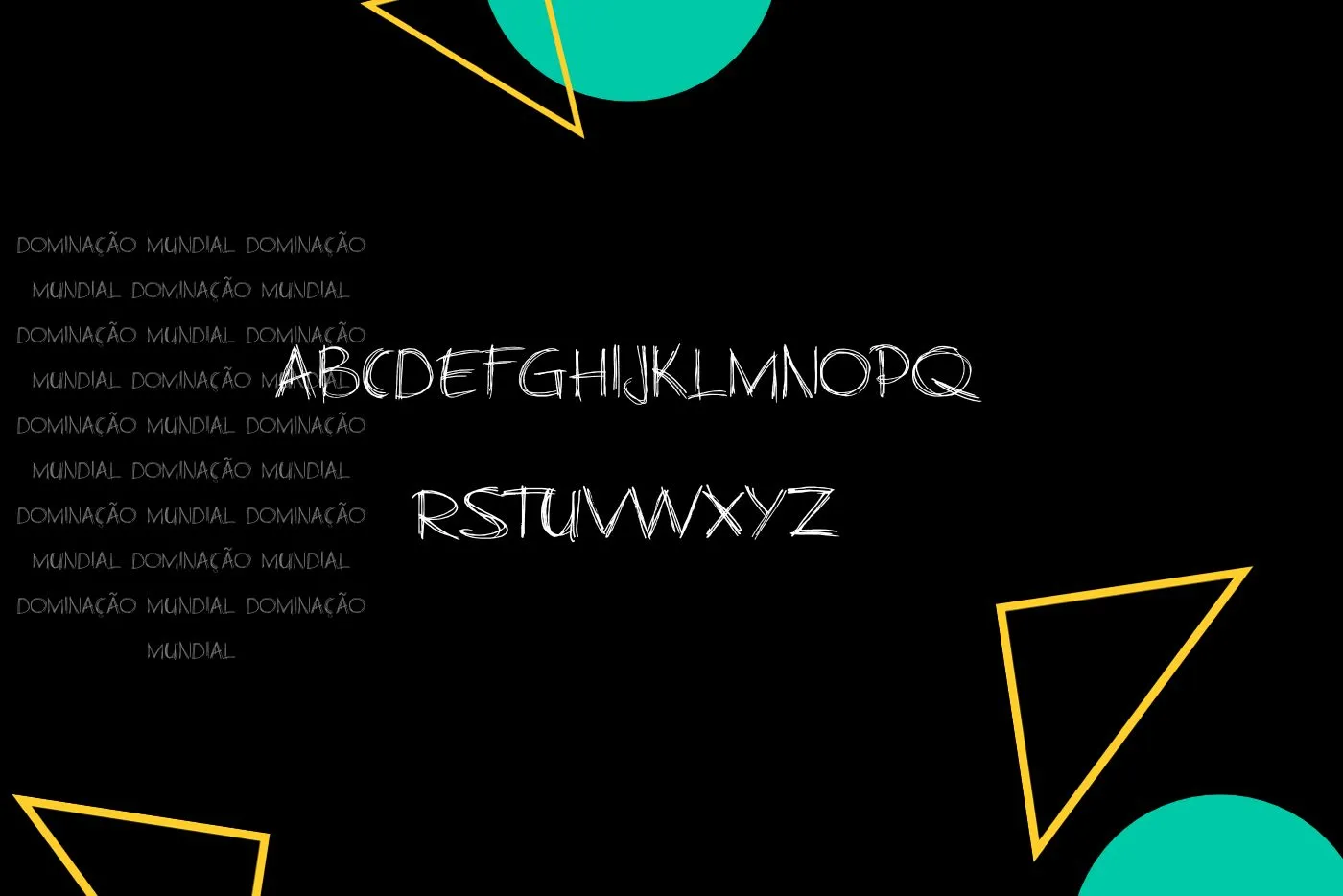
A fonte Business As Usual é uma fonte de script. Foi desenhado por Hanoded e é uma escolha que se destaca pelo seu carácter sério e profissional. Seu design é uma combinação de formas geométricas e linhas limpas que lhe conferem um aspecto moderno e organizado. É perfeito para combinar com sua alternativa. Fonte Road Rage é mais adequado para esse propósito. Esta fonte é particularmente adequada para uso em contextos empresariais e corporativos, onde a comunicação precisa transmitir confiabilidade e seriedade.
Uma das características marcantes desta fonte é sua legibilidade. As letras são cuidadosamente projetadas para garantir que cada caractere seja facilmente reconhecido, tornando-as uma escolha sólida para documentos, relatórios e materiais de marketing que precisam comunicar informações de forma clara e eficaz. Seus caracteres são consistentes e bem espaçados, garantindo que o texto fique visualmente equilibrado e de fácil leitura em diferentes tamanhos e mídias.
Emparelhamento Com a Fonte Business As Usual
Para uma combinação eficaz, é importante escolher uma fonte secundária que complemente seu estilo limpo e profissional. Aqui estão algumas opções de emparelhamento que podem funcionar bem:
- Fonte Arial: É uma fonte sem serifa amplamente reconhecida por sua legibilidade e simplicidade. Ele pode ser usado para títulos e cabeçalhos em combinação para criar um contraste entre os elementos proeminentes e o corpo do texto.
- Fonte Geórgia: É uma fonte serifada que pode criar um contraste interessante. É especialmente adequado para uso em documentos impressos, proporcionando uma sensação de formalidade e sofisticação.
- Fonte Open Sans: É uma fonte sem serifa fácil de usar que equilibra perfeitamente a legibilidade com um toque de modernidade. Pode ser usado para criar um contraste suave em materiais de marketing e apresentações.
Família de Fontes Business As Usual
- Business As Usual Regular
Melhores Usos da Fonte Business As Usual
As melhores e mais utilizadas aplicações desta fonte são:
- Logos e marcas de luxo.
- Títulos em materiais impressos e digitais.
- Design de moda e etiquetas de produtos.
- Convites e papelaria elegante.
- Campanhas publicitárias glamorosas.
- Posts e conteúdo de mídia social marcante.
- Embalagens de produtos de alta qualidade.
- Letreiros e placas em estabelecimentos comerciais.
- Criação de arte tipográfica personalizada.
- Títulos de matérias em revistas e livros.
Vista da Fonte Business As Usual
Qual é a fonte Business As Usual?
É uma fonte de script. Foi desenhado por Hanoded e é uma escolha que se destaca pelo seu carácter sério e profissional.
Qual par de fontes oferece o melhor resultado quando combinado com a fonte Business As Usual?
O emparelhamento ajuda o designer a criar designs elegantes. Seu estilo elegante pode ser aprimorado combinando-o com a fonte Russel Square.
A fonte Business As Usual é adequada para o corpo do texto?
Não é a escolha ideal para o texto principal devido ao seu estilo de design mais ornamentado, mas pode ser adequado para títulos e cabeçalhos.